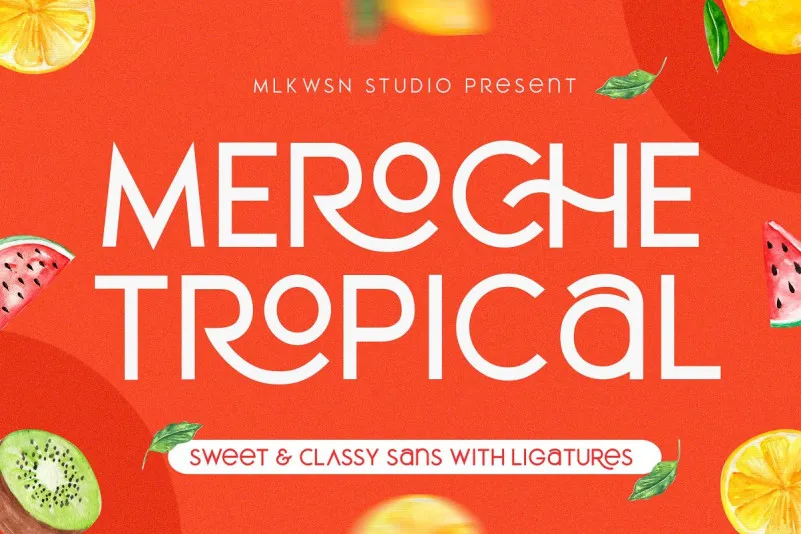
Meroche Sans é uma nova escolha para designers que procuram um tipo sem serif com ares frescos e elegantes. Idealmente adaptado para logotipos, identidades visuais, embalagens, cartazes, convites e até mesmo para conteúdo digital como instastories, Meroche Sans oferece 4 pesos: fino, regular, médio e bold. Além disso, a família inclui mais de vinte combinações alternativas de letras que proporcionam uma aparência suave e sofisticada, tornando-a perfeita para sua próxima campanha ou projeto. Desenvolvida e compartilhada pelo designer MLKWSN, Meroche Sans é uma opção versátil que não se limita ao papel impresso, mas também abrange as mídias digitais atuais, permitindo que seus projetos brilhem tanto digital quanto em papel.